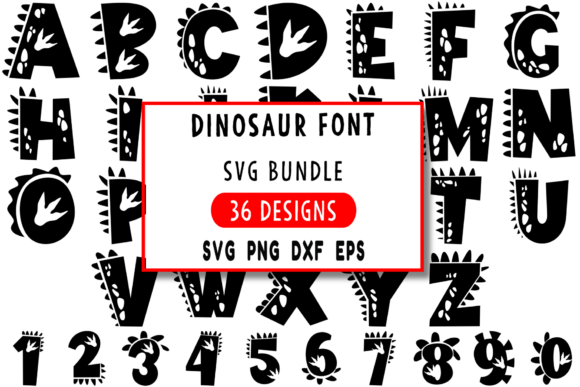
Dinosaur Font SVG, Dinosaur Alphabet SVG
Ulasan Detalhada: Dinosaur Font SVG & Dinosaur Alphabet SVG
Se você procura adicionar um toque jurássico e divertido aos seus projetos criativos, o Dinosaur Font SVG Bundle é a escolha perfeita. Este pacote traz um conjunto completo de fontes e alfabetos temáticos de dinossauros, ideal para trabalhos voltados ao público infantil, festas de aniversário, decoração de salas de aula e muito mais.
Principais Benefícios
- Linhas suaves e limpas: garantem cortes precisos no Cricut, Silhouette ou qualquer outro software de recorte.
- Organização por cores: facilita a edição e a personalização de cada letra ou número.
- Versatilidade: use em camisetas, canecas, pôsteres, cartões, adesivos e até sinalização personalizada.
Aplicações Ideais
- Decoração de festas de aniversário de dinossauros
- Artesanato educativo – alfabetos e números para salas de aula
- Criação de nomes personalizados em camisetas ou canecas
- Projetos de scrapbooking e papercraft temáticos
Por que escolher este bundle?
Em resumo, o Dinosaur Font SVG Bundle oferece tudo que designers, professores e criadores de festas precisam para transformar ideias simples em projetos extraordinários, cheios de energia pré-histórica. Baixe agora e dê vida ao seu próximo trabalho com a magia dos dinossauros!